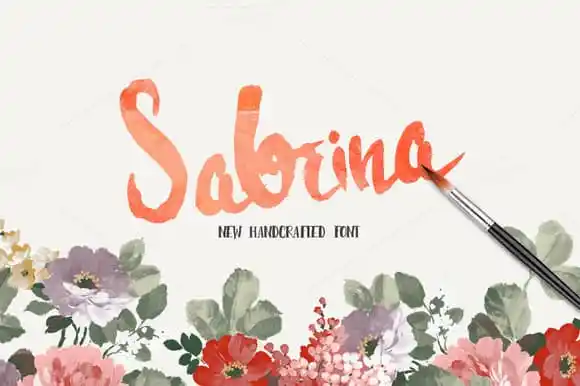
A fonte ‘Sabrina Handmade Font’ é uma opção única para designers que procuram uma mão-direita versátil para trabalhos criativos e pessoais. Criada pelo designer Typeface, ela traz uma mistura de estilo artesanal com elegância moderna, perfeita para textos tanto digitais quanto impressos. Ideal para design gráfico de alta qualidade, sua letra cuidadosamente elaborada oferece um toque de personalidade em qualquer projeto. A Sabrina Handmade captura a essência da arte manual sem perder o encanto que os elementos modernos dão às fórmulas do futuro. Compreender as nuances desta fonte é uma experiência gratificante para quem busca expressar sua voz única, seja através de textos ou imagens. Com suas linhas curvilíneas e detalhes delicados, a Sabrina Handmade se destaca na categoria de Brush Fonts. Seja você um designer digital, um artista gráfico ou até mesmo um escritor que valoriza a essência artística em cada palavra, esta fonte oferece uma maneira única de expressar seu estilo pessoal.